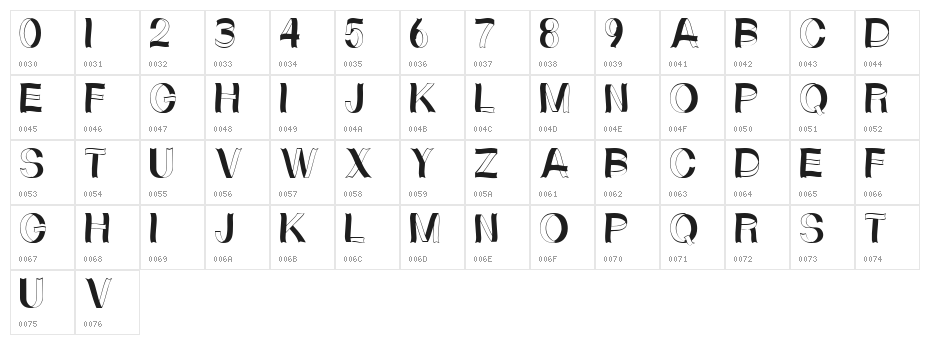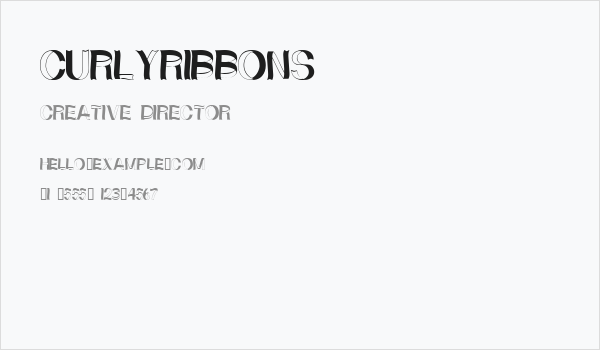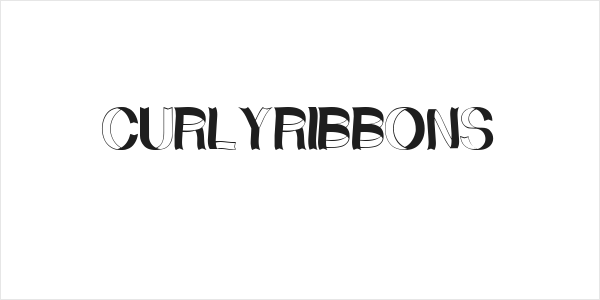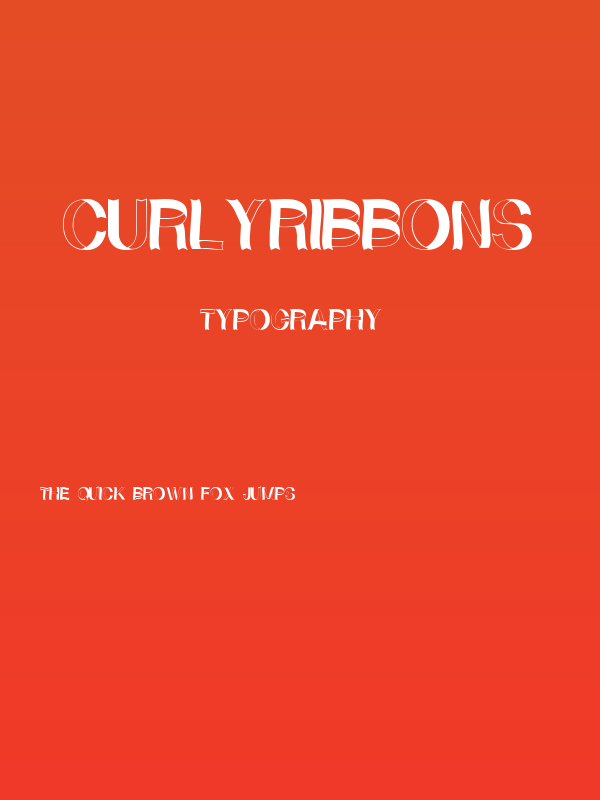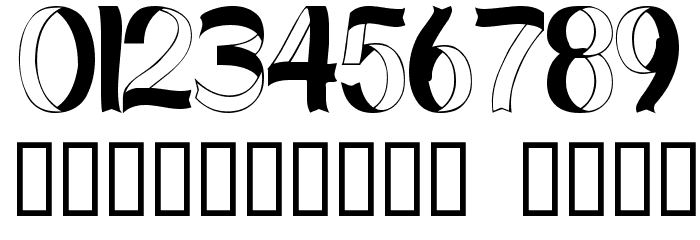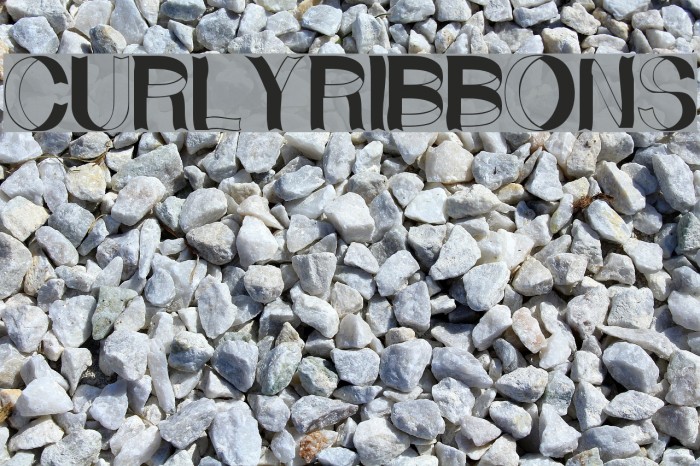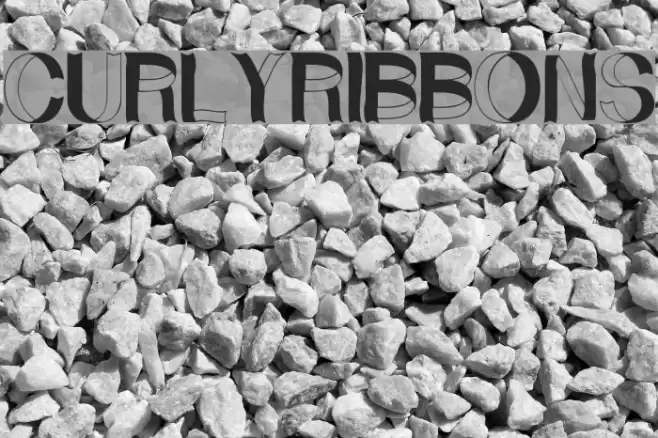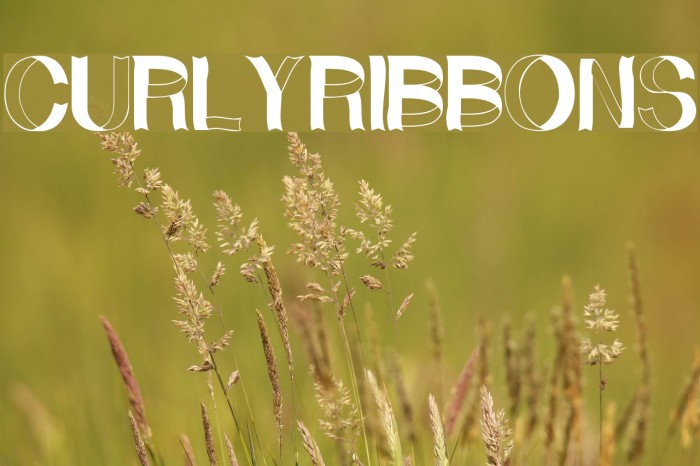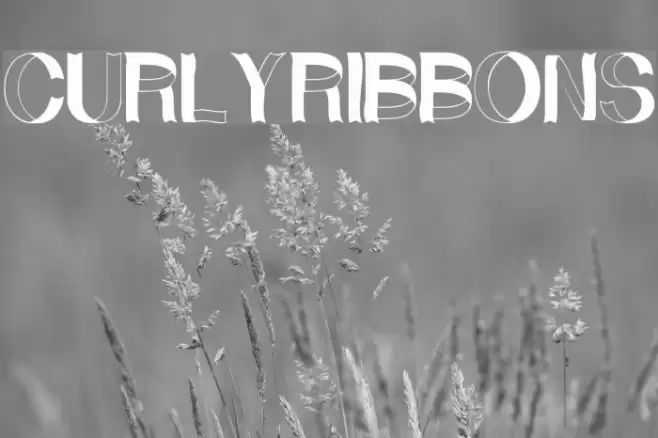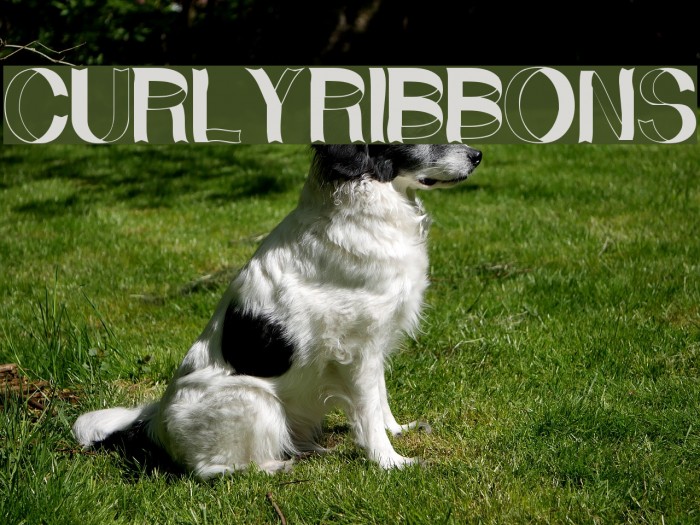
CurlyRibbons Font
| Рекомендуемые проекты | Ideal for creative projects such as greeting cards, invitations, posters, and branding materials that require a whimsical and artistic touch. |